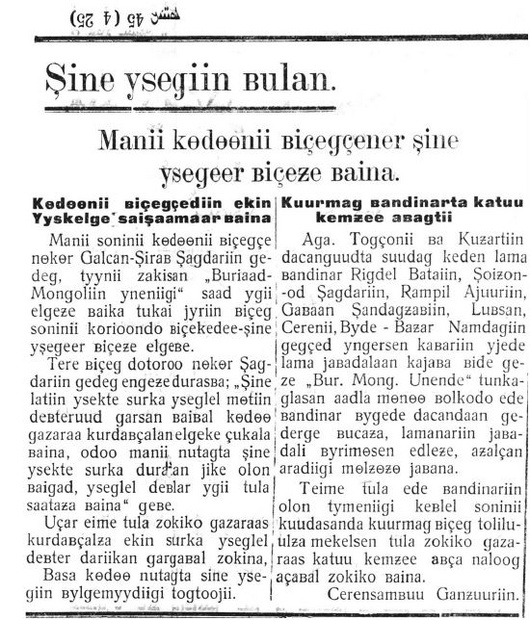
Woher kommt der Strich im Z?
Ich habe mich gerade gefragt, warum das handgeschriebene Z oftmals einen kleinen Strich in der Mitte hat. In der Lateinischen Ausgangsschrift, die ich in der Schule gelernt habe, hat das große Z einen Mittelstrich, das kleine nicht. Ich mache heute in meiner Handschrift in beide einen Strich und ziehe dann beim kleinen z von diesem Mittelstrich aus weiter. (Das ist wohl aber ursprünglich nicht so gedacht, da in der LA gerade das kleine z keinen Mittelstrich hat.) Weiß jemand, woher dieser Strich stammt bzw. welche Funktion er eigentlich haben sollte?
solcherart zierart (wie auch bei einigen der strich über dem u) soll die unterscheidungsfähigkeit der buchstaben fördern. wobei mir auf anhieb nur die 2 einfällt, die ich mit einem Z verwechseln könnte...
Beim Strich über dem u leuchtet es ja ein, da dies sonst oftmals wirklich vom n nicht zu unterscheiden wäre. Aber beim z sehe ich eigentlich auch keine Verwechslungsgefahr mit einem anderen Buchstaben… :-?
C S L könnten bei einer etwas zügigeren schreibe oder -- bei mir standard -- geschmiere verwechselungspotential bieten. vielleicht sogar das J.
oder aber es ist ein erbe des Z (mit unterlänge und schleife auf der grundlinie) der kurrentzeit, die sich via sütterlin und sütterlin-latein erhalten hat...
wobei mir auf anhieb nur die 2 einfällt, die ich mit einem Z verwechseln könnte...
Der Kritzel über dem U hat auch eine historische Erklärung: Ursprünglich war es ein übergeschriebenes o, bezeichnet also den ehemaligen Diphthong uo in Wörtern wie Buͦb oder fluͦchen (aber nicht in Wörtern wie Flug oder Stube). Ähnlich wie die Schreibung ie später auch in Wörtern wie Sieg oder diese verwendet wurde, die historisch gesehen gar nie den ursprünglichen Diphthong ie aufwiesen, so wurde später auch das in Fällen verwendet, die historisch gesehen gar nie ein uo aufwiesen (nämlich einfach in allen Fällen von u).
Der Querstrich beim Z hat aber keine derartige historische Erklärung, die ihn auf einen ursprünglich eigenständigen Buchstaben zurückführen würde. Gibt es nicht auch (Hand)Schriften, wo auch das grosse H einen (vertikalen) Querstrich aufweist?
Ich werfe mal noch in den Raum, dass der Mittelstrich hin und wieder auch bei der Ziffer 7 zu sehen ist.
Vielleicht gibt es ja ähnliche Beweggründe bzw. Zusammenhänge bzgl. der Anwendung beim Z und hilft uns weiter. :-?
Ich hatte natürlich die Unterscheidung nach Genus gemeint. Sie mag zwar seit dem 18. Jahrhundert im Hochdeutschen unüblich geworden sein, aber die Form zwo hat sich in verschiedenen Dialekten gehalten, sei es, weil die Genus-Unterscheidung beibehalten, oder sei es, weil die feminine Form zwo statt der Neutrum-Form zwei verallgemeinert wurde. Und ausserdem sind ja die älteren Texte mit der Form zwo nicht einfach verschwunden.
Übrigens gibt es auch die Charaktere Ƶ und ƶ.
Vielleicht, dies ist aber nur so eine Idee von mir, diente das Strichelchen im Z einfach dazu den Schreibfluß etwas zu bremsen. Das Z kann man ja recht flüssig schreiben und möglicherweise war der nachfolgende Buchstabe, durch den noch vorhandenen Schwung, dann bei den Schülern etwas gekritzelt. Durch den Querstrich mußte nun aber erst einmal abgesetzt werden und der folgende Buchstabe war dann ev. etwas ordentlicher.
Übrigens gibt es auch die Charaktere Ƶ und ƶ.
Über die war ich überhaupt erst auf meine Frage gekommen. Die wurden nämlich zumindest in den 20er und 30er Jahren in den sogenannten „neuen Lateinalphabeten“ in der Sowjetunion für den Lautwert [ʒ] (also wie in Genie oder Journalist) verwendet. Man hatte da dann parallel nebeneinander ein z und ein . Aber diese Alphabete (bzw. Orthographien) waren nur kurzlebig, Ende der 30er Jahre wurde dann generell für alle Sprachen auf das kyrillische Alphabet umgestellt.
Als Beispiel hier ein kurzer Text vom September 1930 auf Burjatisch:
aber vielleicht ist das Z mit Strich ja letztlich auch eine Übernahme aus dem griechischen Alphabet und hier vom Ξ, Dass wenn ich mich recht erinnere in Handschrift oft wie ein Z mit Strich aussieht.
Das halte ich für sehr unwahrscheinlich. Erstens sind ein Ξ und ein Z ja zwei völlig verschiedene Buchstaben (und ein Z gibt es im griechischen Alphabet ja auch). Und zudem müßte sich der Strich dann ja durch die ganze Schriftgeschichte ziehen. :-)